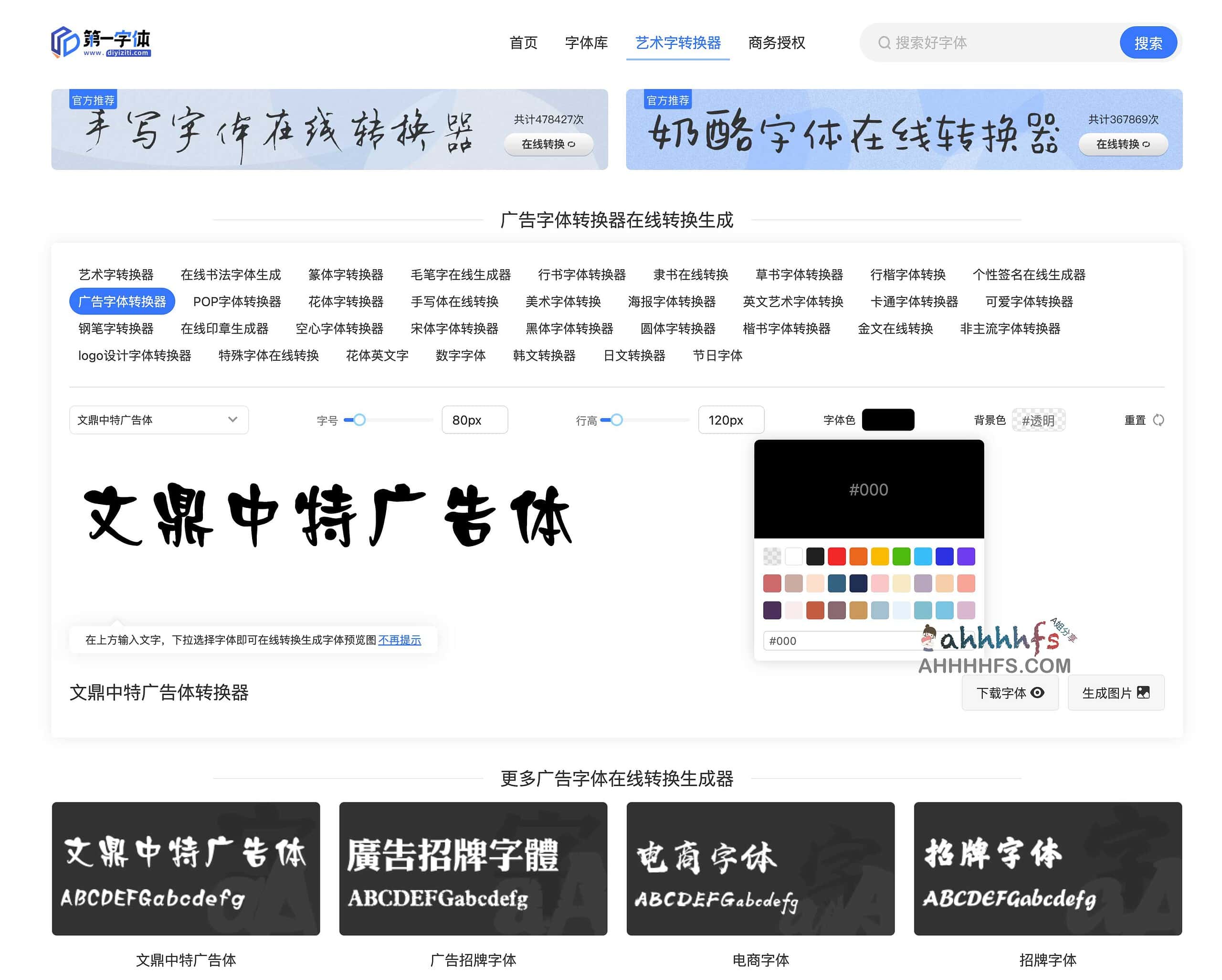
找不到心仪的字体或无法直接转换格式?试试这款在线字体转换与下载工具
在设计海报、制作 PPT 或排版文档时,你是否经常遇到这种困境:想要一种极具个性的书法体或艺术字,但电脑里安装的字体太少,且手动安装新字体既繁琐又容易导致系统卡顿?
认识第一字体网
如果你需要快速生成视觉冲击力强的文字,第一字体网 提供了一个高效的解决方案。它不仅是一个字体下载平台,更是一个强大的 在线字体转换与生成工具
该平台涵盖了极其丰富的字体库,用户无需下载安装即可在网页端直接完成转换。其核心功能包括:
• 艺术字生成: 涵盖书法字体、毛笔字等多种风格。
• 多样化字体库: 提供草书、篆体、连笔字以及 POP 字体等中英双语资源。
• 便捷转换: 通过在线转换器,快速将普通文字转化为具有设计感的艺术字体。